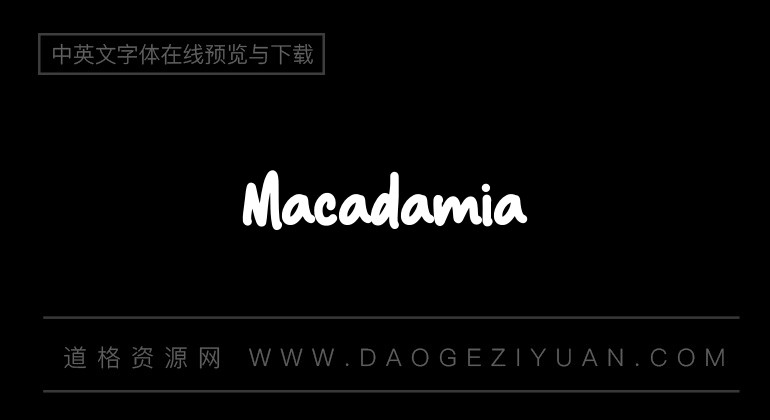
Macadamia
? Macadamia 字体是一款具有明显西方风格的字体,它具有细腻、优雅的线条,具有良好的可读性,适合用于报纸、杂志、书籍和其他印刷品的出版。它的字形结构清晰,可以在大小不同的文本中保持一致的风格,同时兼顾了美观和可读性,使用它可以让文本更加简洁、清晰。此外,Macadamia 字体还可以与其他字体组合使用,以营造出更加丰富的视觉效果。
Macadamia是一款非常不错的手写艺术字体,具有很好的视觉感,适合于文化类的宣传设计、商业类品牌的广告和产品包装设计以及个性化文字排版等较多场景。